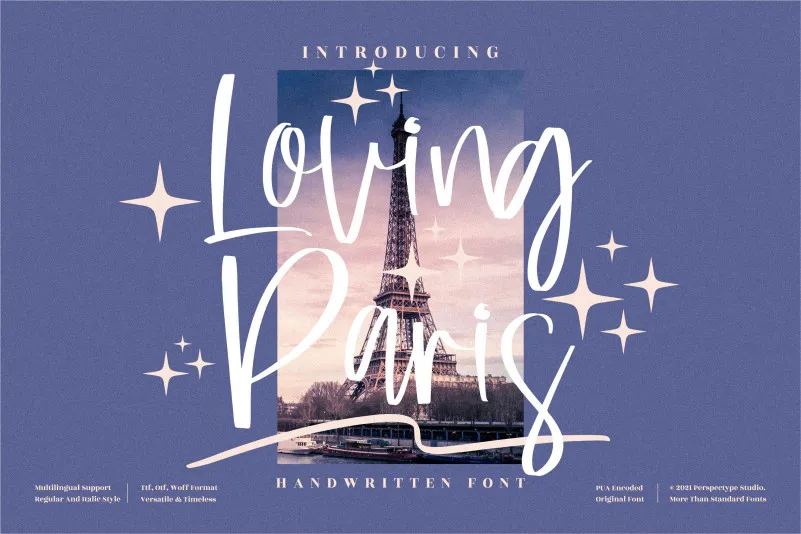
Loving Paris Font – Download Grátis
Esta é uma fonte script delicada que transmite elegância e sofisticação. Perspectype especialmente criou essa fonte para designers buscando um aspecto atraente e renovador nos seus trabalhos gráficos. Suas curvas suaves, traços finos e textura levemente flutuante fazem dela uma escolha ideal para adicionar um toque único aos designers que desejam trazer frescura às suas criações de texto ou arte digital. Lembre-se, a font “Loving Paris” não só oferece um visual envolvente e natural, mas também adiciona um ar de elegância ao seu próximo projeto, tornando-a uma opção indispensável para qualquer designer que valoriza beleza e refinamento na sua comunicação visual.